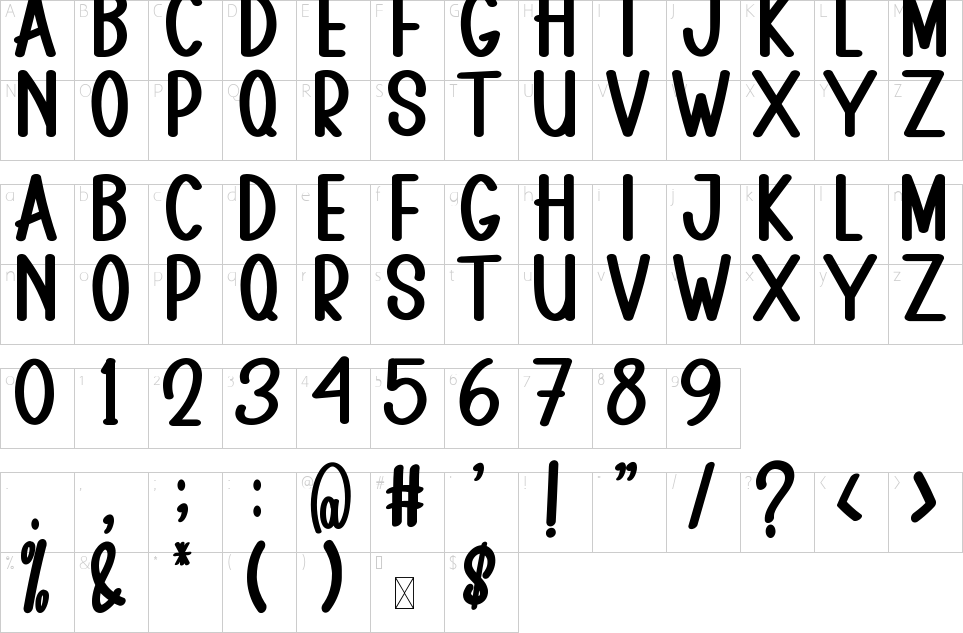
A fonte ‘Journal Handmade’ é uma fonte gráfica disponível gratuitamente para Windows e Mac, criada pelo designer InermediaSTUDIO. Desenvolvida com um estilo casual e artesanal, essa fonte traz uma sensação de naturalidade e elegância, ideal para uso em jornais, blogs pessoais e até até em criações gráficas de design livre. Com 516 downloads desde seu lançamento, ‘Journal Handmade’ é uma escolha versátil para quem busca personalidade em suas criações. Suas linhas suaves e traços delicados complementam perfeitamente a atmosfera relaxada e descontraída do jornalismo online, oferecendo um touch artesanal que complementa o conteúdo de uma maneira única. Não espere apenas, experimente a ‘Journal Handmade’ e transforme seu design em algo ainda mais autêntico e singular.